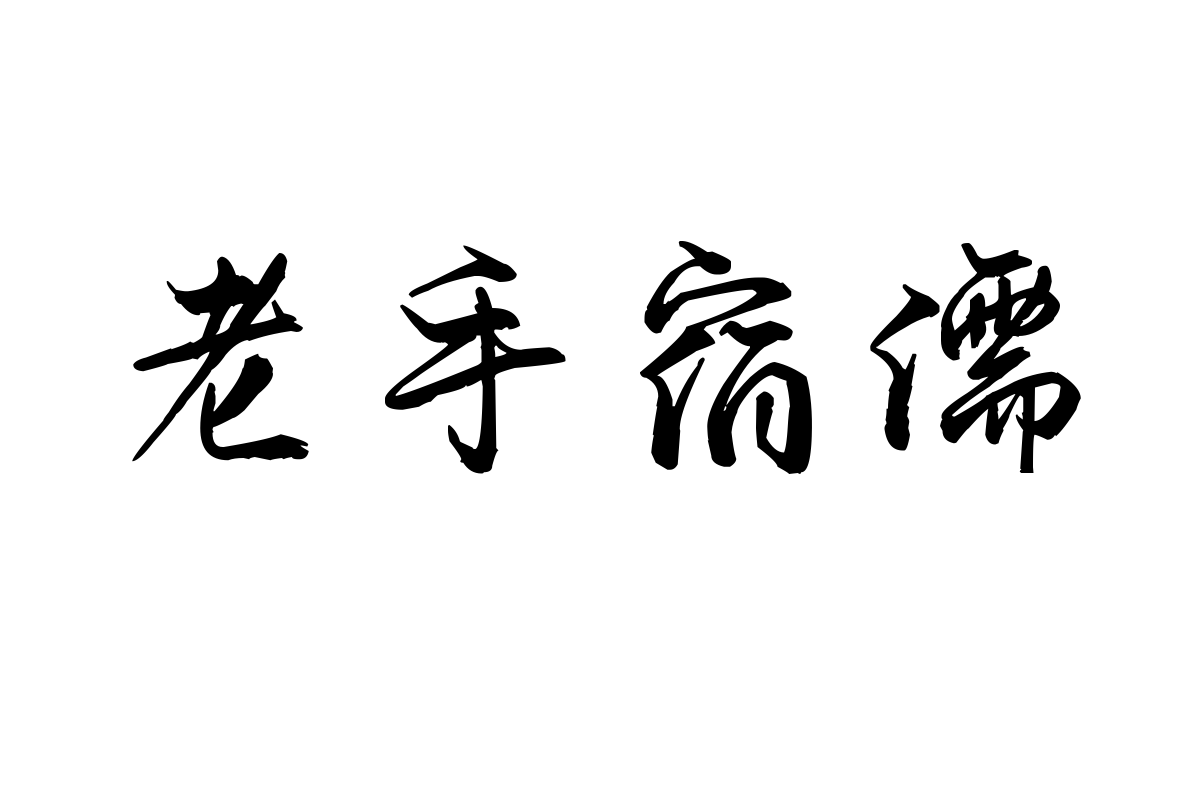
“也字工厂游龙行楷”是一款由“也字工厂”公司设计的字体。这款字体具有独特的风格和特点,适合用于各种设计项目,包括广告、标志、包装、网站等。
这款字体的特点如下:
1. 字形独特:游龙行楷的字形独特,线条流畅,给人一种优雅的感觉。
2. 笔画清晰:每个笔画都清晰可见,易于阅读和识别。
3. 结构紧凑:字体结构紧凑,适合需要强调重点的设计项目。
4. 适应性强:这款字体适用于多种场景,无论是商业还是艺术设计,都能展现出其独特的魅力。
总的来说,”也字工厂游龙行楷”是一款非常实用的字体,适合用于各种设计项目。